え?こんなデザインも使えるの?! ジャンル別にわかる、モリサワ新書体2022【和文編】
新書体……この言葉を聞いてワクワクする方もそうでない方も、ぜひ最後までスクロールしていただきたい!!というのも今年はなんと、目で見て楽しいデザイン書体をはじめとする超充実のラインナップでお届けするんです。
この記事では、各書体の特徴と魅力を全力でお伝えしていきたいと思います。時間がない方は “目次” から気になる書体をクリックしてみてくださいね。
今回は【和文編】ということで、和文の新規書体をご紹介します。
通常和文を分類する際は ”明朝体” や “ゴシック体” といったカテゴリで分けますが、今回はグラフィカルな “デザイン書体” が多いため、より印象が掴みやすいように独自のジャンルで分けてみました。それがこちら!
大胆なデザインが多い「インパクト」、あどけなさや遊び心を感じさせるゆるっとした「ゆるポップ」、レトロ可愛い雰囲気を纏った「ロマン」、筆や活字の雰囲気を残したクラシカルな印象の「オールド」です。
それぞれのジャンルごとに、各書体の特徴と合わせて解説していきますので、ぜひ自分の “推しフォント” を見つけてみてください。
1. 大胆な「インパクト」を与えるならこんな書体
ゲームやコミックなど、コンテンツの世界観を演出するシーンなどで活躍しそうなパワフルな迫力がある書体たち。画像からもなんだか強烈な個性が伝わってきます。
イカヅチ
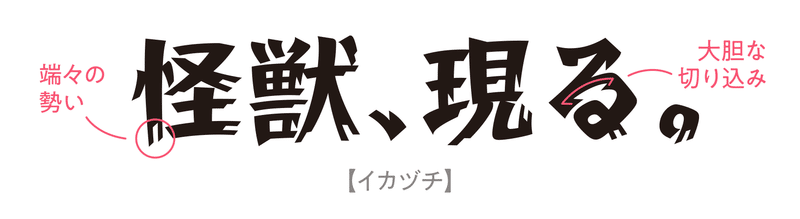
「イカヅチ」は、肉筆感のある大胆なデザインが特徴の書体です。太く張りのあるエレメントに掠れのような装飾を施すことで、見る人に強いインパクトを与えます。大声で何かを伝えるようなシーンや目立たせたい箇所をより一層引き立てることができ、コミックやテレビテロップなど、大きなサイズで使っていただくと映えます!
くろまめ
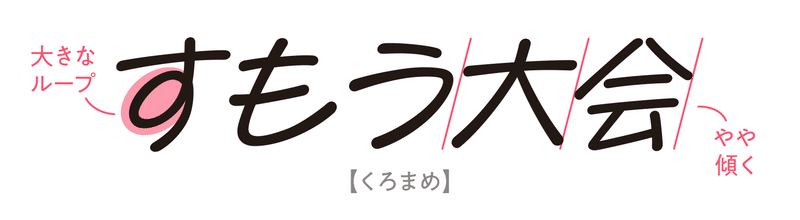
「くろまめ」は、広くデザインしたふところと、“ループ” を強調したかなが特徴の明るい雰囲気を持つ書体です。書体名を検討する際も、なるべくループが見せられるような名前で検討していました。
ループがある文字以外ももちろん魅力的ですし(例えば「も」の伸びやかさもいいですよね)、全体的に少し傾いていることによる手書きの勢いなどにも注目いただきたいです。
翠流アトラス(R/M/B)
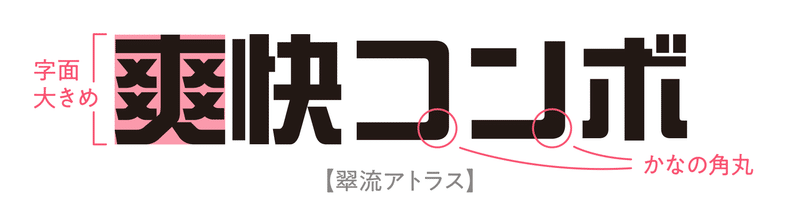
ジャンル別画像の中でも四角さが際立っているのが「翠流アトラス」です。ストレートな骨格と大きな字面に対して、一部の漢字のエレメントやかなの四隅に角丸を取り入れることで、硬くなりすぎない印象になっています。ハライがくねっと曲がっているところなんかは、愛らしさすら覚えました(個人の感想です笑)。
ラピスエッジ/ラピスメルト(L/M/B)
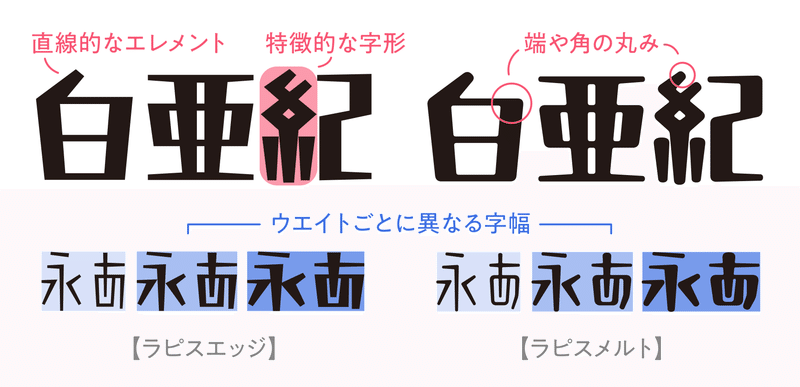
直線のみで構成されたシンプルな設計の「ラピスエッジ」。このラピスエッジの角に丸みを持たせ、かなを自然な骨格にアレンジしたのが「ラピスメルト」です。どちらもウエイトごとに字幅が異なるのが特徴です。
一部の文字では個性的な字形を採用しており、特に「糸」のデザインなんて面白いと思いませんか? 遺跡に掘られた文字みたいですよね…!
これまでも「G2サンセリフ」や「ぶらっしゅ」のように字面が大きくてインパクトのある書体はありましたが、これらの書体が加わることでより幅広い表現が可能になります。
ラピスエッジ/ラピスメルトや翠流アトラスはウエイト展開も豊富なので、ぜひ利用シーンに合った太さを選んでみてください。
2. 遊び心は「ゆるポップ」 な書体たちにお任せあれ
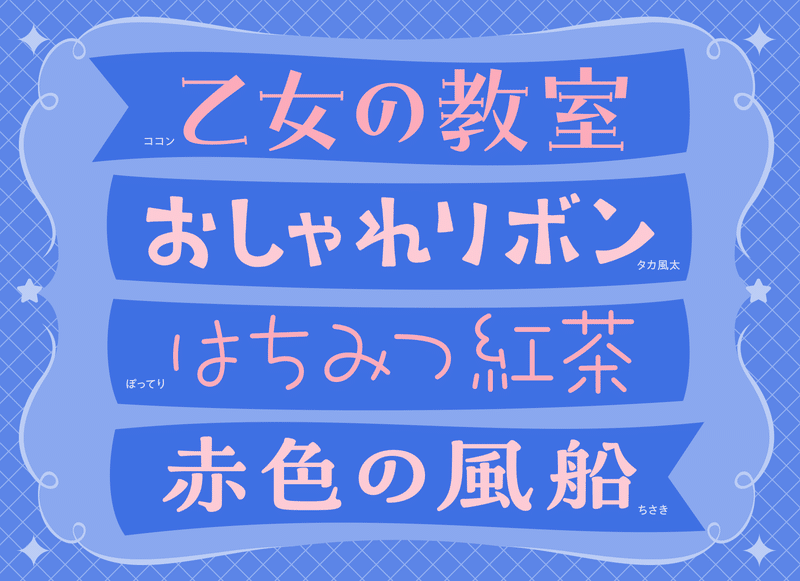
続いて、どこか “ゆるっ” とポップな印象の書体たち。やや字面が小さめで、遊び心のあるデザインが多くなっています。
ココン
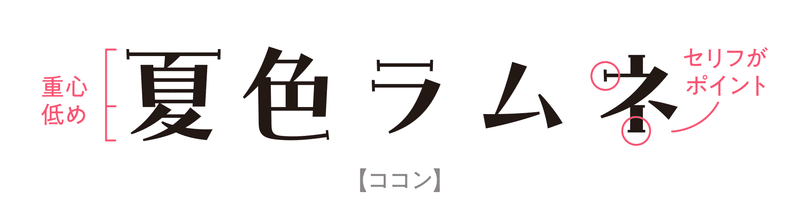
「ココン」は低い重心とやや下にすぼまるプロポーションを持つ、レトロであどけない雰囲気の書体です。横画の両端についたセリフが特徴で、手書き由来の温かさや親しみやすさの中に、エレガントさをプラスしました。
実はこの書体、リリース前にテレビ出演したことがありまして、ようやく皆さまにお届けできるのが楽しみです!
タカ風太
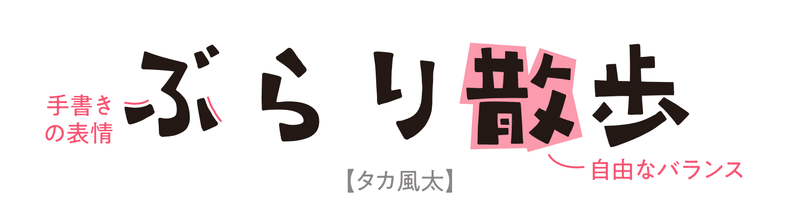
手書きそのままの味わいを残し、自由な印象を与えるのが「タカ風太」。文字のバランスや線の表情を整えすぎないように設計されており、伸び伸びとした親しみやすさを感じさせます。
個々は自由なデザインなのに、文章を打つとまとまって見えるのがフォントのすごいところ…。
ちさき
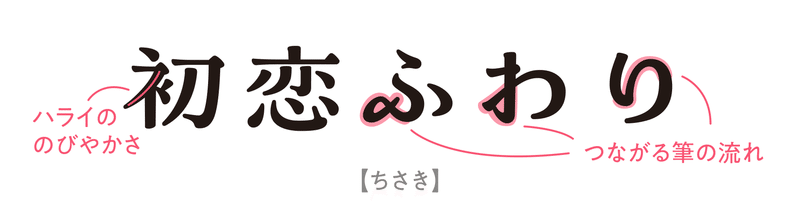
「ちさき」は書き文字や金属活字の要素を取り入れた、古風で可愛らしい明朝体風のデザイン書体です。 平体気味のプロポーションに、漢字の筆おさえやかなの筆脈といった筆のニュアンスとデフォルメされたエレメントを組み合わせることで、レトロな可愛さを演出します。
オールド系の明朝体とも相性がいいので、このあとご紹介するオールド書体で組んだ文章に「ちさき」をポイント使いする!なんてこともオススメですよ。
ぽってり(L/R/M/B)
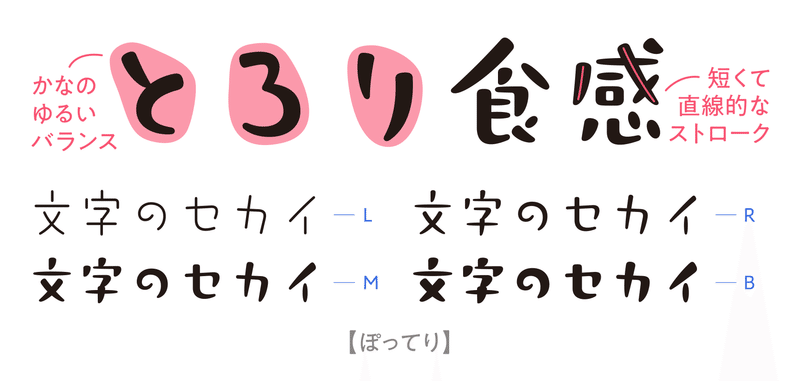
「ぽってり」は、筆ペンで書いた文字をイメージしたゆる可愛い雰囲気の書体です。重心が低くアンバランスな骨格、短く直線的なストロークが、あどけなさや素朴さを演出します。ウエイトが太くなるにつれてコントラストが際立ち、かなり表情が変わるのもポイントです。
続いて、書体名に「プフ」とつくものがあり、これを私たちは「プフ」シリーズと呼んでいます。
統一しすぎない自由な字形と小さめの字面が特徴のデザイン書体ラインナップで、今年は4書体リリース予定です。なんとこのプフシリーズ、書体ごとに “オリジナルキャラクター絵文字” を1文字搭載しており、異体字として選択入力できるんです!
上のプフシリーズ画像のどこかにも隠れているので見つけてみてください!
前置きはここまでとして、それぞれのデザインについて順番にご紹介していきたいと思います。
プフ ホリデー
今回リリースするプフシリーズの中で一番ウエイトが細いのが「プフ ホリデー」です。ペンで手書きしたような明るく親しみやすいデザインで、抑揚のない、しなやかな曲線で構成されています。少し長めの文章なども組むことが可能です。オリジナル絵文字は少し眠そうな “やぎさん” 。
プフ ポッケ
「プフ ポッケ」は、ゴシック体風のデザインながら角の折り返しにカーブ(制作チーム内では“なで肩”と呼んでいました)を取り入れており、力の入りすぎない可愛らしさを表現することができます。オリジナル絵文字はキュートな “どんぐり” !
プフ マーチ
丸ゴシック体風のデザインとやや幾何学的なプロポーションが特徴の「プフ マーチ」は、プフシリーズの中では字面がやや大きく整頓されたイメージを持ちます。もちもちとした線質で、やわらかい印象の書体です。オリジナル絵文字は驚いたような口がおちゃめな “きのこ” 。
プフ ピクニック
「プフ ピクニック」は、手書きの骨格をもつ太いゴシック体風のデザインです。あえて文字の大きさを揃えすぎないことで、ほどよいゆるさを残しています。はつらつとした明るい雰囲気を演出するのが得意な書体です。オリジナル絵文字は、ピクニックに是非とも連れていきたい “おにぎり” です。
“ゆるポップ” に分類した書体は実は、社内のデザイン公募から選ばれた書体が多く、独自のファミリー構成やデザイン設計をしています。デザインに力の抜けた雰囲気をプラスしたいような場面で、書体選びの幅が広がること間違いなしです!
3. レトロ可愛いは「ロマン」な書体で作れちゃう
続いて、個性的な装飾を取り入れたレトロかわいい書体をまとめて「ロマン」と名付けました。
オズ
装飾性が高く、ブラックレター風の雰囲気を持つのが「オズ」。直線的な骨格でありながらも折り返しの角は丸く設計しており、硬くなりすぎないユニークなデザインになっています。
白のアリス
「白のアリス」は、平筆由来の西洋風ストロークとクリアで柔らかなエレメントをもつ「赤のアリス」にラインを入れ、さらに装飾性を高めた書体です。視覚的にシャドウのような効果があり、そのまま打ち出すだけでロゴのように決まってくれます。
「オズ」と「白のアリス」は元々 “かな書体” でしたが、漢字を加えた総合書体としてリリースされます。
かなの雰囲気を漢字に反映するにあたっては、かなのデザインを分解して要素を抜き出して制作していました(これが結構大変なんです)。かなと漢字のマッチングにもぜひご注目ください。
翠流ネオロマン/翠流デコロマン
続いて、「翠流ネオロマン」と「翠流デコロマン」はやや低めの重心をもつスクエアな骨格の漢字を共通とした、ハイコントラストな書体です。
起筆・収筆にうろこのような装飾を施した「翠流ネオロマン」はすっきりとした可愛らしさのあるデザインです。
「翠流デコロマン」は「翠流ネオロマン」の “かなと記号類” に装飾を施しており、くるんとしたカールや濁点のキラキラがより華やかな印象を与えます。
どこかレトロな雰囲気もあり、こんな文字でメニューが書いてある喫茶店に行ってみたくなっちゃいますね〜。
各書体、画像の中では世界観強めなワードチョイスをしていますが、こんな文章も合う!という予想外の使われ方を見てみたいラインナップでもあります(「赤のアリス」の “うなぎ” のような……詳しくはこちらをご覧ください笑)。
是非いろいろなシーンで使ってみてください!
4. 「オールド」書体を使いこなして機微を演出
筆や活字の雰囲気を残したクラシカルな印象の書体も充実!
本文組みができる書体から見出しに使えるような太めの書体まで、幅広い用途をカバーするラインナップです。
霞青藍(L/R/M/B)
「霞青藍」は、楷書体の要素を色濃く残すローコントラストなオールドスタイルの明朝体です。横画やハライの伸びやかさを強調したふところの締まった骨格の漢字に、1940〜60年代の活字にインスパイアされたかなを合わせました。欧文は15世紀末の活字の骨格をベースにしています。
全体的に無骨さを感じるデザインになっていて、キザな文章などが似合いそうですよね。横画が少し太めのため視認性も高い書体です。
霞白藤(L/R/M/B)
「霞白藤」は、筆書きのスピード感を活かした流麗でハイコントラストなオールドスタイルの明朝体です。かなは築地5号系および36ポ仮名をベースに、欧文は16世紀のフランスやオランダ活字の骨格をベースにしつつも、細部のエレメントをシンプルにすることで現代的な印象に仕上げています。
「霞青藍」「霞白藤」は漢字の “骨格” は共通していますが、ハライやハネの先端に武骨な印象がある青藍に対して、白藤はスッと抜けるようなエレガントな処理になっています。また、漢字・かな・欧文それぞれ、活字を再解釈してデザインしたものを組み合わせていまして、詳細については追々noteの記事で深掘りしていきたいと思います。お楽しみに!